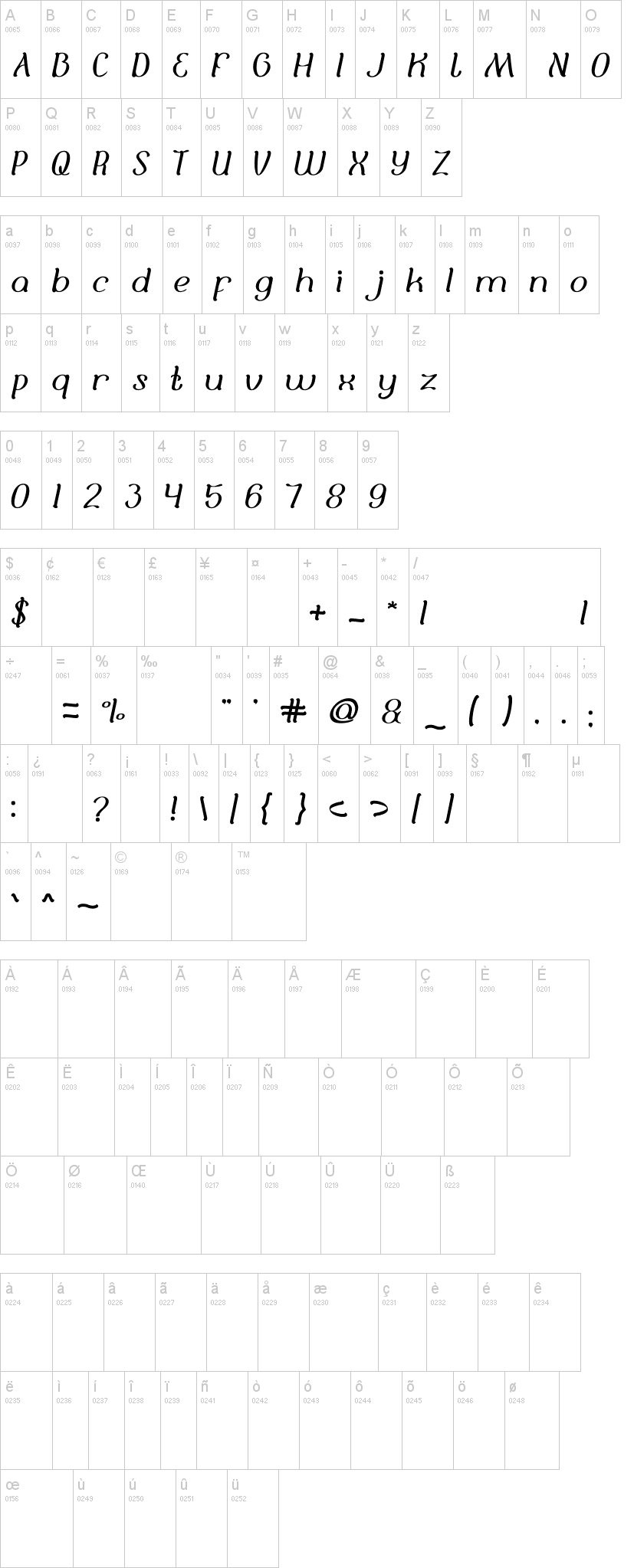
? Adore You 字体是一款新款的手写字体,它具有柔和、浪漫、温暖的特点,适合用于浪漫爱情的场景,或者用于向恋人表达爱意的场景。它具有细腻的线条,柔和的节奏,丰富的表情,有助于更好地表达情感。内容介绍
Adore You是一款非常不错的手写艺术字体,具有很好的视觉感,适合于文化类的宣传设计、商业类品牌的广告和产品包装设计以及个性化文字排版等较多场景。